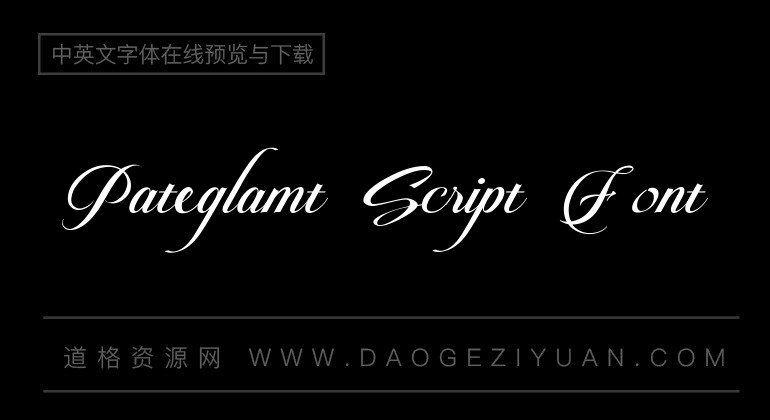
Pateglamt Script Font 是一种手写风格的字体,具有流畅的笔画和自然的手写风格。该字体包括大写字母、小写字母、数字和标点符号,可以用于多种设计项目,如海报、名片、网站设计等。此字体的特点是笔画流畅、柔和、自然,适合营造浪漫、文艺、温馨等氛围。内容介绍
Pateglamt Script Font是一款非常不错的手写艺术字体,具有很好的视觉感,适合于文化类的宣传设计、商业类品牌的广告和产品包装设计以及个性化文字排版等较多场景。